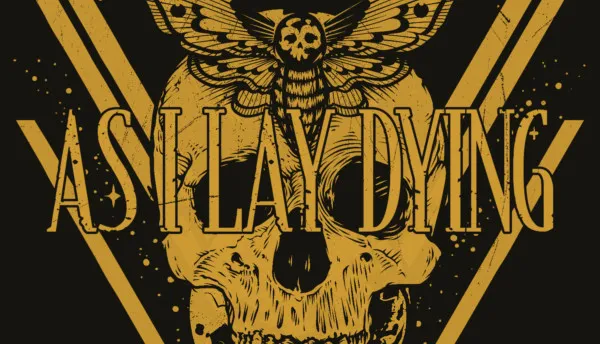
A fonte ‘As I Lay Dying’ oferece uma experiência visual única e atraente para designers que buscam uma serif sem ser tradicionalmente formal. Fundamentada na arte contemporânea, esta fonte traz um toque moderno às letras serifadas, mantendo o estilo elegante esperado no tipo de serif. Suas linhas delicadamente arredondadas e acabamento suave tornam-a perfeita para aplicações variadas, como design editorial, criação de logotipos ou qualquer projeto que valorize um aspecto sofisticado e refinado. O designer lj.design é conhecido por inovar no design gráfico, oferecendo uma gama completa e versátil de fontes, permitindo a designers profissionais e amadores explorarem novas maneiras de expressão visual. Com os termos de uso claros fornecidos na página inicial do designer, os usuários podem usar ‘As I Lay Dying’ para propósitos comerciais sem problema algum. Para aqueles que buscam um toque único e uma experiência imersiva em seu design, a fonte ‘As I Lay Dying’ é perfeita. Um complemento de alta qualidade para qualquer designer gráfico, esta fonte atende às necessidades das pessoas que valorizam criatividade e modernidade no mundo do design.